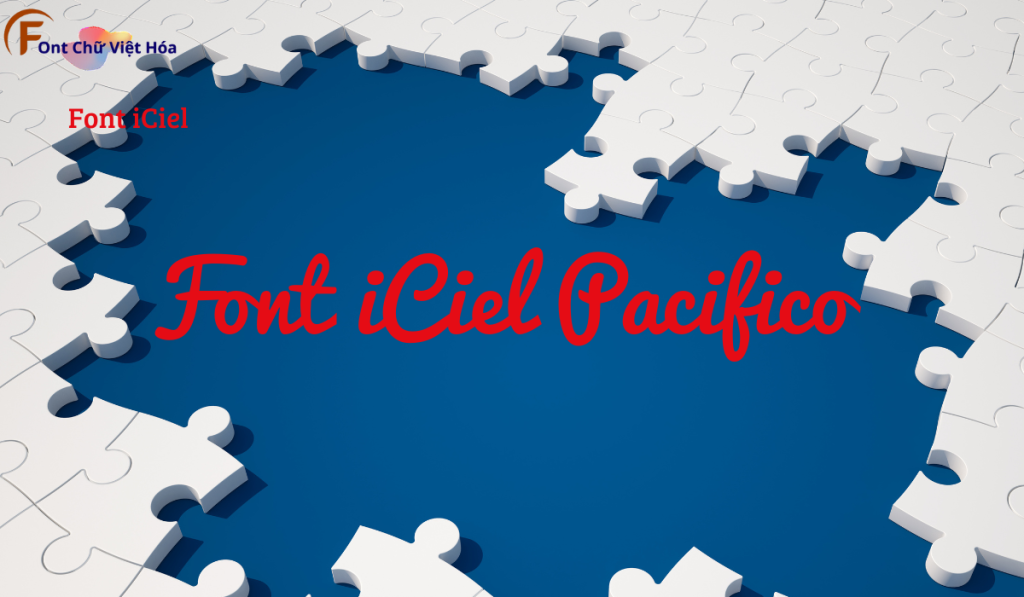
Font iCiel Pacifico Việt Hóa
Ngôn ngữ: Tiếng Việt, Latin
Bộ Font: iCiel
Phân loại: cá tính, độc đáo
Kiểu chữ: chữ viết tay
Font iCiel Pacifico Việt Hóa, thuộc bộ font iCiel, là font chữ viết tay cá tính, nổi bật với các nét chữ độc đáo và mềm mại. Font này có các đường nét tự nhiên, dễ đọc, tạo cảm giác thân thiện và sáng tạo. Font iCiel Pacifico Việt Hóa lý tưởng cho các dự án thiết kế như poster, logo, và bao bì sản phẩm. Việc Việt hóa font giúp người dùng dễ dàng tích hợp vào các thiết kế tiếng Việt, mang lại sự tiện lợi và nâng cao tính thẩm mỹ.